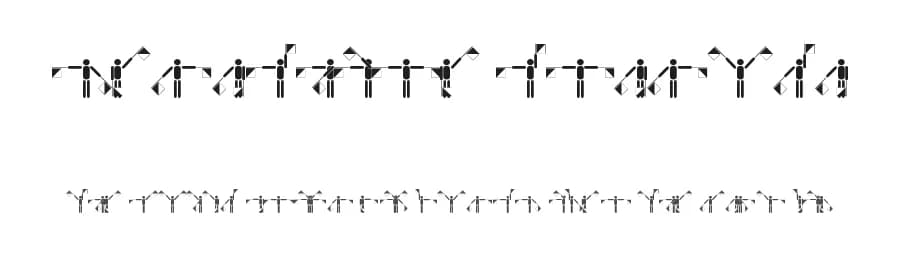
About Semaphore Pramuka Font
font ini berisi semaphore pramuka, maaf susunannya berantakan
(wikipedia.org) Semafor adalah suatu cara untuk mengirim dan menerima berita dengan menggunakan bendera, dayung, batang, tangan kosong atau dengan sarung tangan. Informasi yang didapat dibaca melalui posisi bendera atau tangan. Namun kini yang umumnya digunakan adalah bendera, yang dinamakan bendera semafor. Pengiriman sandi melalui bendera semafor ini menggunakan dua bendera, yang masing-masing bendera tersebut berukuran 45 cm x 45 cm. Bentuk bendera yang persegi merupakan penggabungan dua buah segitiga sama kaki yang berbeda warna. Warna yang digunakan sebenarnya bisa bermacam-macam, namun yang lazim digunakan adalah warna merah dan kuning, dimana letak warna merah selalu berada dekat tangkai bendera. Pada awal abad ke 19, semafor digunakan dalam komunikasi kelautan.